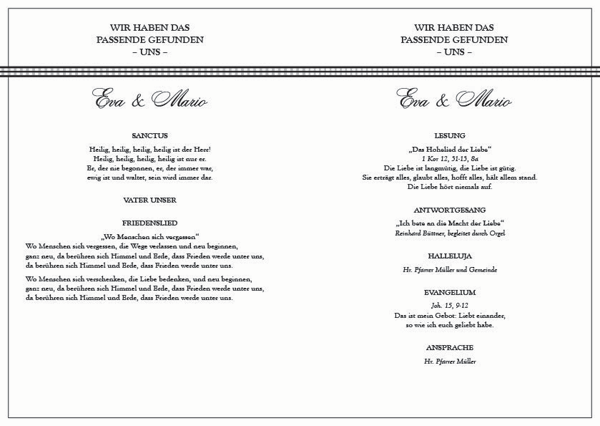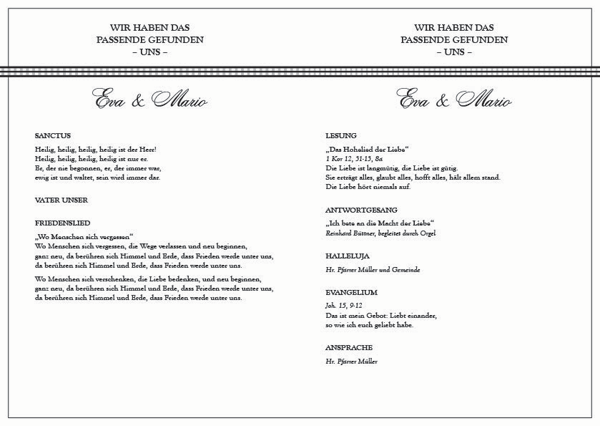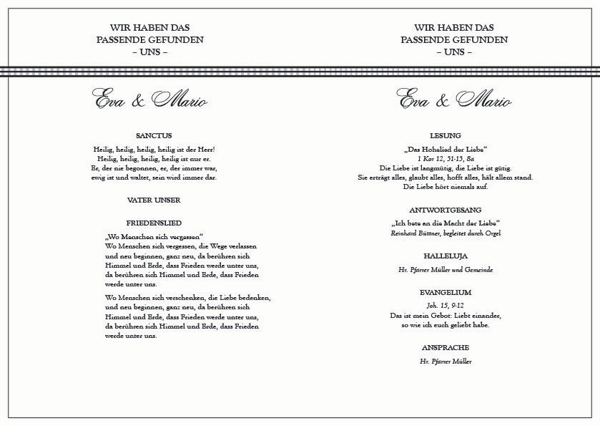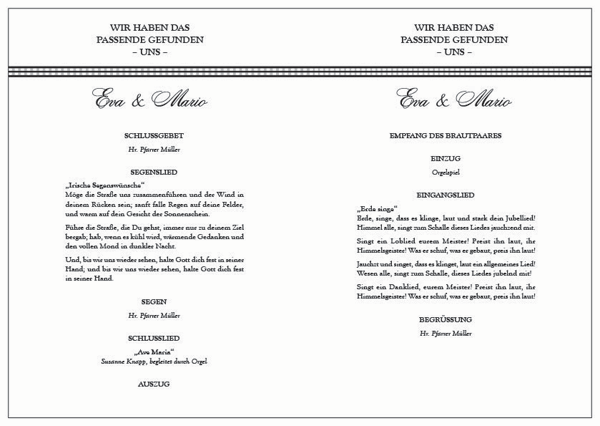
[Mitglied Sunn…] Geschrieben Juni 6, 2012 Teilen Geschrieben Juni 6, 2012 Hallo Zusammen, mache für eine Bekannte die Hochzeitsgestaltung. Bei den Einladungs- und Menükarten ist der Text (Headline, Subheadline und Copy) immer mittig gesetzt. Jetzt sitze ich über das Kirchenheft. Auch hier habe ich den gesamten Text mittig platziert. Nun möchte aber meine Bekannte die einzelnen Lieder (Strophen und Refrains (ohne Noten)) für eine bessere Lesbarkeit linksbündig gesetzt haben. Die Liedertexte sind aber nicht separat vom restlichen Text platziert, sondern befinden sich mitten im Text. Somit finde ich persönlich die Mischung aus linksbündigem und mittigem Text nicht wirklich schön. Den gesamten Text jedoch linksbündig zu setzen, wäre dann nicht mehr gemäß CD bzw. passend zu den restlichen Gestaltungssachen. Andererseits muss man sagen, dass die Einladungs- und Menükarten jeweils mit einer Buchschraube (wie ein Pantone-Fächer) zusammengehalten werden. Die Kirchenhefte werden einfach nur zusammengetackert. Demzufolge könnte man doch sagen, man macht den Text nur linksbündig, da andere Technik und anderes Format? Was sagt Ihr? Für Tipps oder Ratschläge wäre ich sehr dankbar! Vielen Dank schon mal und LG Link zu diesem Kommentar
[Mitglied 4e7a…] Geschrieben Juni 7, 2012 Teilen Geschrieben Juni 7, 2012 meinetwegen lässt sich linksbündiger sehr wohl mit mittigem text mischen. ich sähe beispielsweise die linke satzkante des liedtextes bündig mit der mittelachse … vorausgesetzt, dein konzept, deine gestaltung, die zeilenlängen … lassen diese möglichkeit von ihrem rhythmus (und, und, und) her zu. tatsächlich beurteilen lässt sich aber gestaltetes erst, wenn man es sieht. in diesem sinne … grüße Link zu diesem Kommentar
[Mitglied 5800…] Geschrieben Juni 7, 2012 Teilen Geschrieben Juni 7, 2012 Bei längeren Texten würde ich generell auf zentrierten Satz verzichten. Um trotzdem die zentrierte Anmutung der restlichen Sachen beizubehalten könnte man auch auf Blocksatz zurückgreifen. Das macht dann allerdings Probleme, wenn die Liedertexte versweise umgebrochen werden sollen ... Zentriert und linksbündig gemischt finde ich persönlich auch nicht gut. Aber zwischen den Medien sollte man sich die Freiheit geben etwas anders auf die Textmenge und -Art eingehen zu können. Link zu diesem Kommentar
[Mitglied Sunn…] Geschrieben Juni 7, 2012 Themen-Ersteller Teilen Geschrieben Juni 7, 2012 Vielen lieben Dank für die schnellen Antworten. Eure Vorschläge und Anmerkungen haben mir geholfen! Ich hab jetzt mal drei Varianten ausprobiert (siehe Anhang). Mein persönlicher Favorit wäre die zweite Variante (den gesamten Text linksbündig setzen). Headline und die Namen würde ich mittig belassen. Die erste Variante (V3) würde auch noch gehen, oder? Hier würde ich die linke Satzkante des Liedtextes immer mit dem Titel des Songs beginnen lassen, was ginge, da immer nur ein Lied auf einer Seite vorkommt. Bei zwei Liedern hätte man dann einen Versatz, was unruhig werden dürfte. Den Liedtext mit der Mittelachse bündig setzen geht leider vom Format, Platz etc. nicht. Könnten so die erste und/oder zweite Variante funktionieren? LG Link zu diesem Kommentar
[Mitglied mori…] Geschrieben Juni 7, 2012 Teilen Geschrieben Juni 7, 2012 Mir persönlich gefällt Variante 3 besser. Ich würde allerdings den Textrahmen nach links verschieben und schmaler machen, so dass er in etwa ein Flucht mit dem Text darüber bildet. Tschau Stefan Link zu diesem Kommentar
[Mitglied Diet…] Geschrieben Juni 7, 2012 Teilen Geschrieben Juni 7, 2012 Überschriften mittig zu setzen scheint ein Gesetz bei Laien, ging mir früher ja auch nicht anders. Allerdings könnte ich mir die Überschriften-Schrift in diesem Fall nur schwer linksbündig vorstellen. Für mich geht bei Deinen Beispielen Variante 2 gar nicht. Am besten fände ich Variante 1, allerdings dürfte der Text vom Friedenslied nicht so weit eingezogen sein, sondern müsste etwa so unter der Überschrift stehen, dass es auch mittig wirkt. Link zu diesem Kommentar
[Mitglied Sunn…] Geschrieben Juni 8, 2012 Themen-Ersteller Teilen Geschrieben Juni 8, 2012 Vielen Dank für eure Feedbacks. Ich hab mir das Kirchenheft noch mal angeguckt, eure Meinungen gelesen und Herumprobiert. Das Problem bei der ersten Variante hatte ich auch so gesehen, dass der Text zu weit eingezogen war. Vor allem, wenn man dann die restlichen Seiten (wo der Liedtext einfach anders verläuft) gesehen hat, hatte man schon das Gefühl, der Text kippt sehr nach rechts. Den Rahmen außen konnte ich leider auch nicht verändern, da es mehrere Seiten gibt, wo die Liedtexte unterschiedlich lang sind und verlaufen. Der Rahmen wäre ja dann immer gesprungen (von Seite zu Seite). Deshalb hab ich nun einen festen Textrahmen (mit Blocksatz anstelle von Flattersatz) für den Liedtext gewählt und diesen dann mittig zum restlich zentrierten Text gesetzt. Mit dem Ergebnis bin ich jetzt ganz zufrieden. LG Link zu diesem Kommentar
[Mitglied ayse…] Geschrieben Juni 17, 2012 Teilen Geschrieben Juni 17, 2012 ein weiteres Blatt einhängen. Dann zumindest wäre der zentrierte Satz wieder solo. Link zu diesem Kommentar